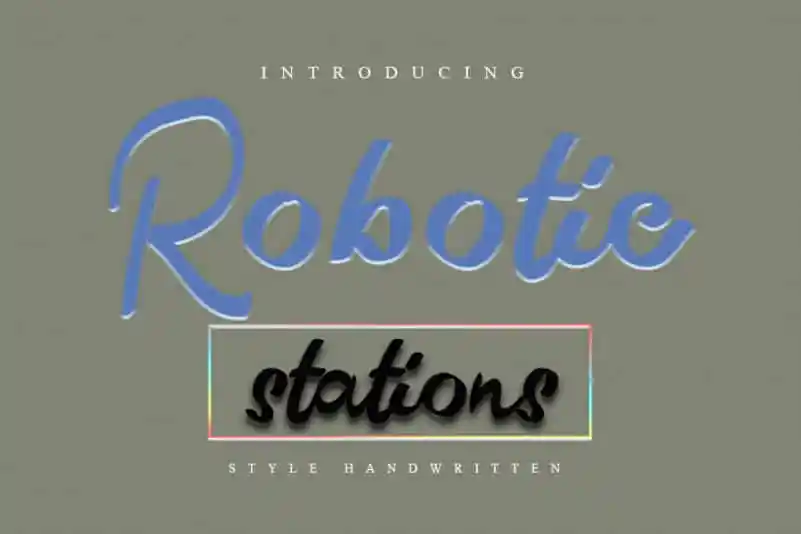
Robotic Stations Display Font – Download Grátis
A Robotic Stations Display Font é uma incrível escolha para designers que buscam um efeito moderno sem deixar de lado a elegância dos textos manuscritos. Mantém seus traços chamativas, mas adiciona um toque contemporâneo e fresco que faz dela uma opção versátil perfeita para múltiplas aplicações. Seja em letras para cartões ou títulos para embalagens de papelaria, a Robotic Stations Display Font é uma fonte ideal. Suas linhas diretas e reta, combinadas com uma sensação moderna, oferecem um contraste interessante e dinâmico que torna ela a escolha certa para os designers que buscam estilização em sua tipografia. Sem dúvida, essa Robotic Stations Display Font é uma ótima adição ao seu portfólio de recursos gráficos.